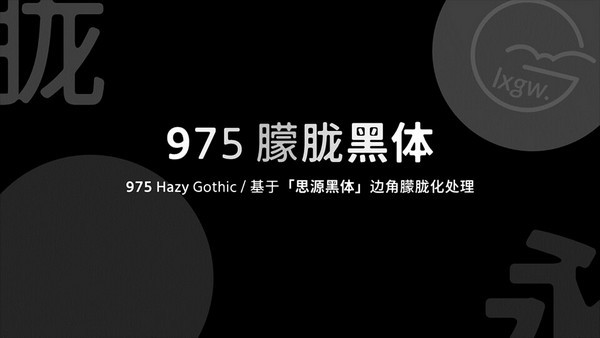
975朦胧黑字体
975朦胧黑体让你的电脑字体别具一格,独特的线条加上加黑处理更有刚劲有力的字体表现还有简单的安装方法轻松更换,适合喜欢更换各种字体的朋友十分值得一试。需要的朋友赶紧来下载吧!
975朦胧黑字体介绍:
975朦胧黑体是一款基于思源黑体边角朦胧化处理的字体,朦朦胧胧产生距离美,进行边角朦胧化之后,字体感觉像墨晕开了一样,产生别样的感受!
975朦胧黑体特点: